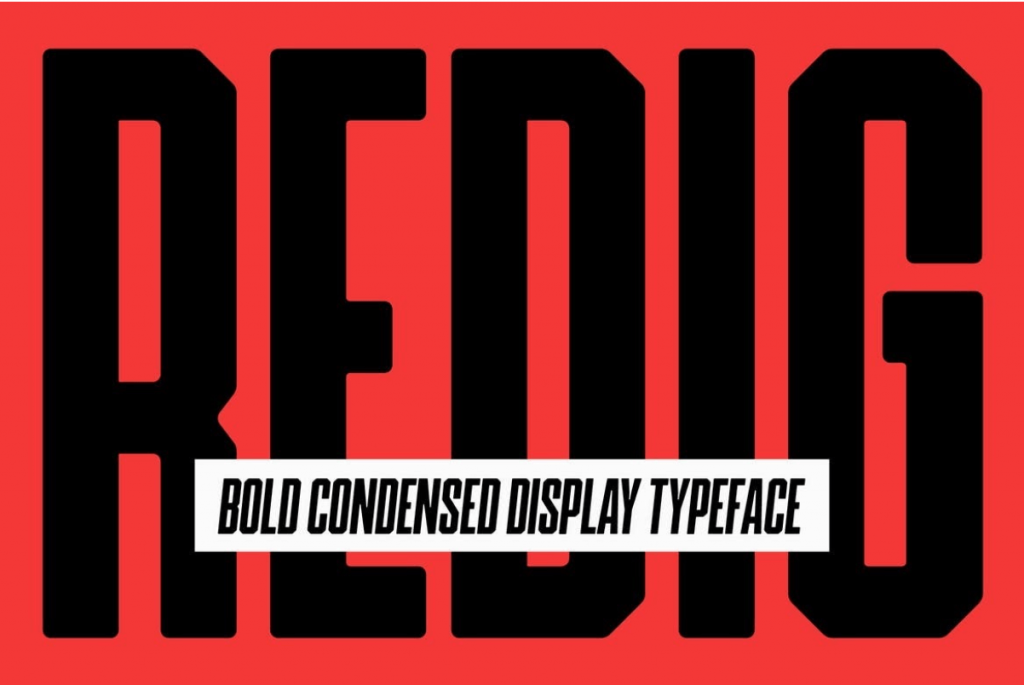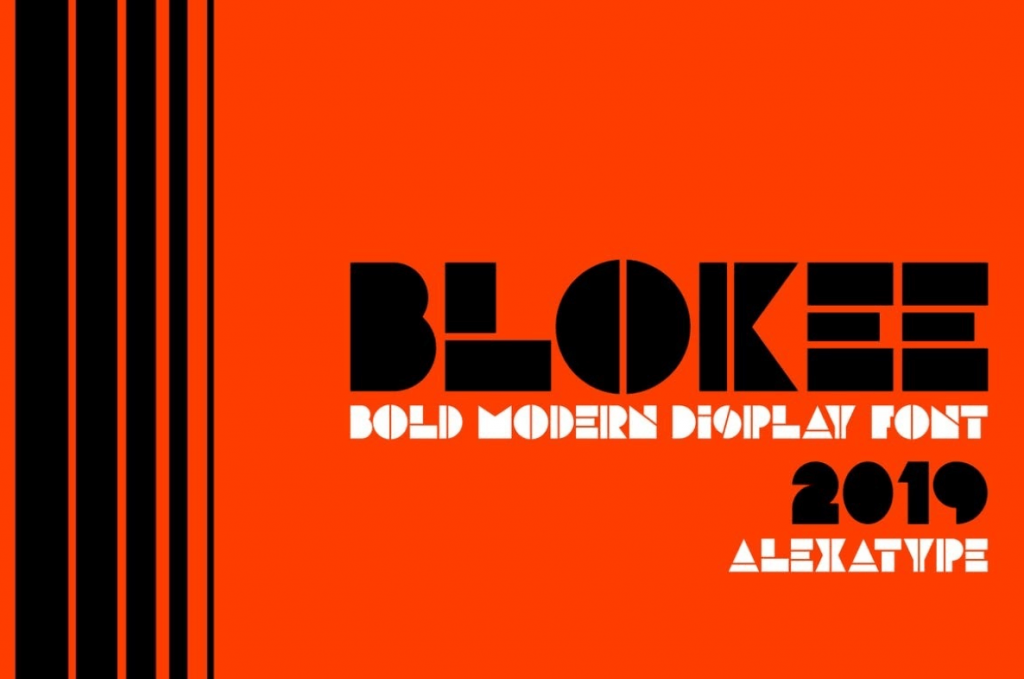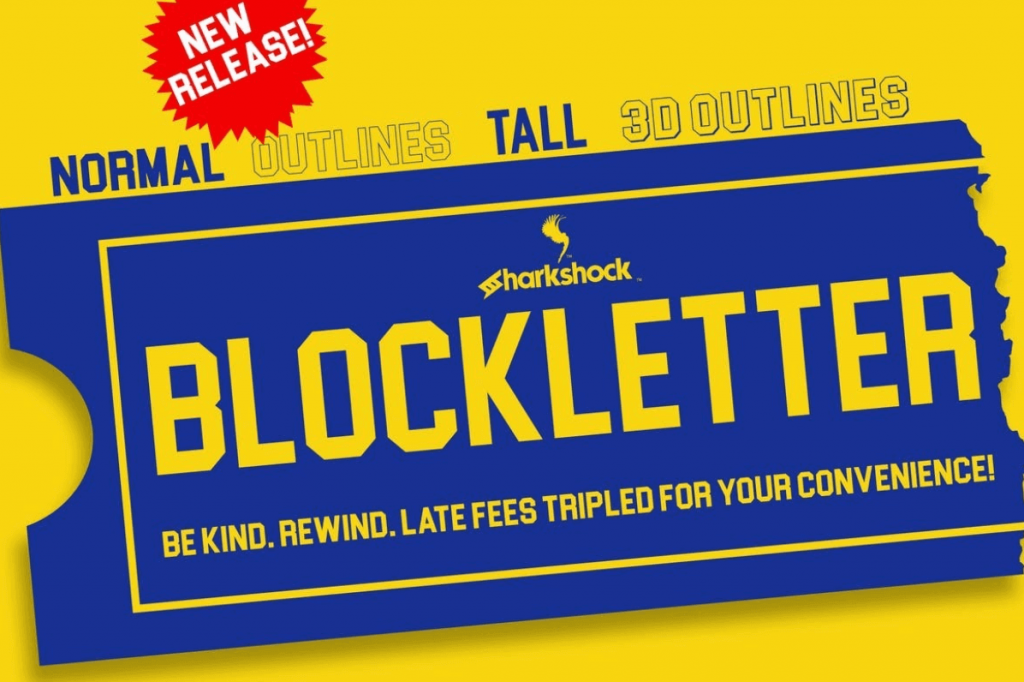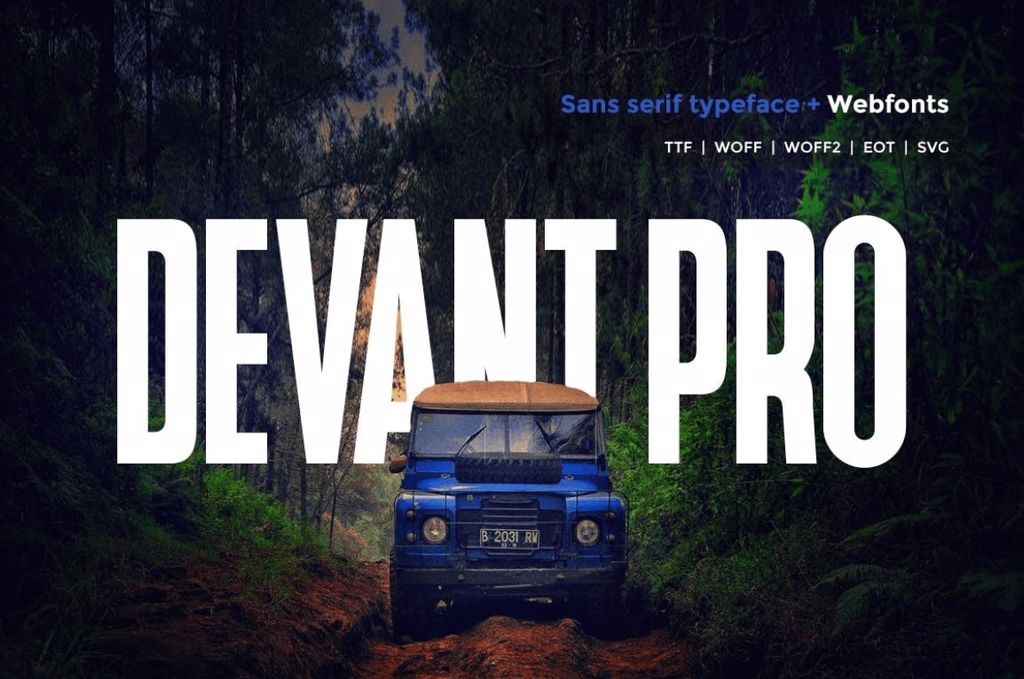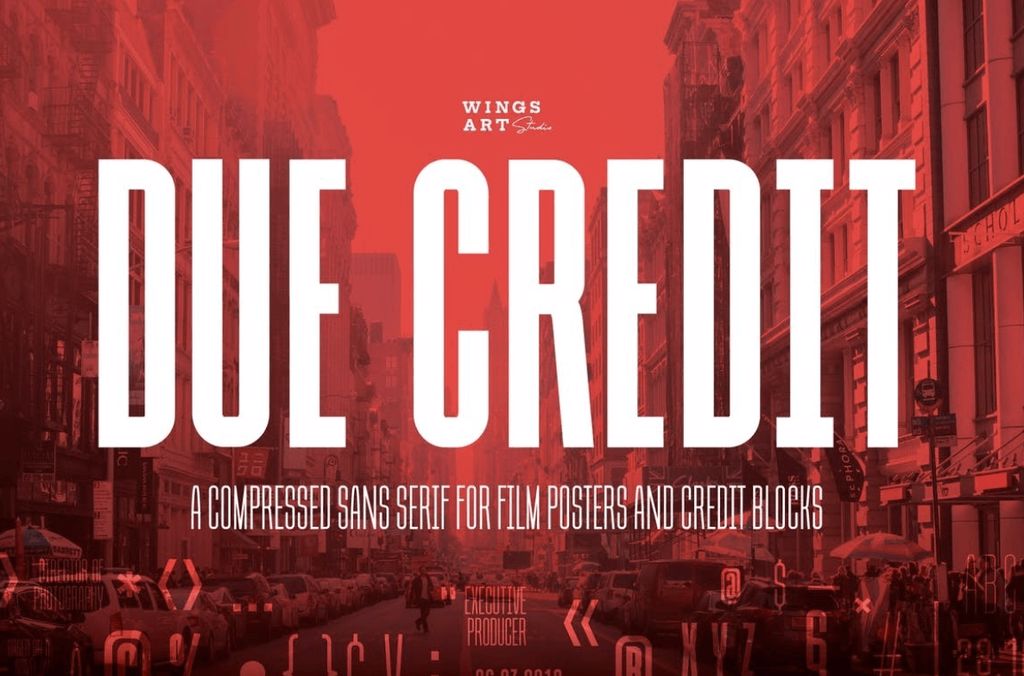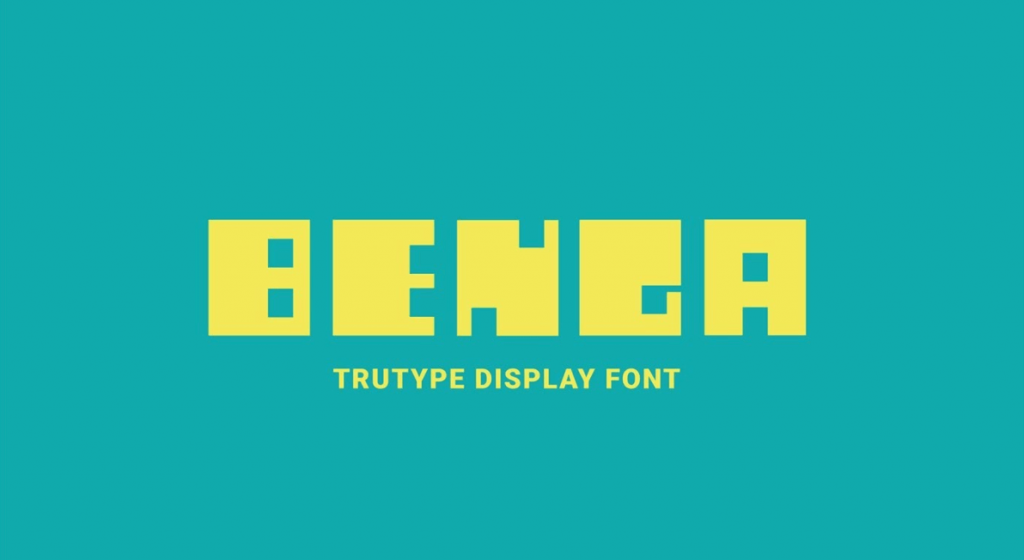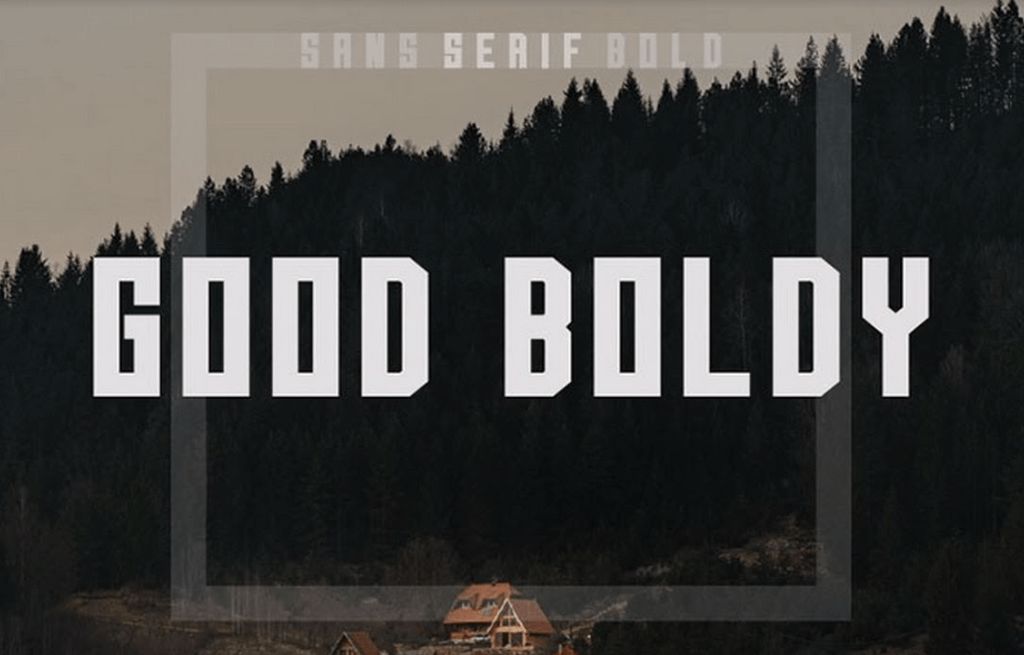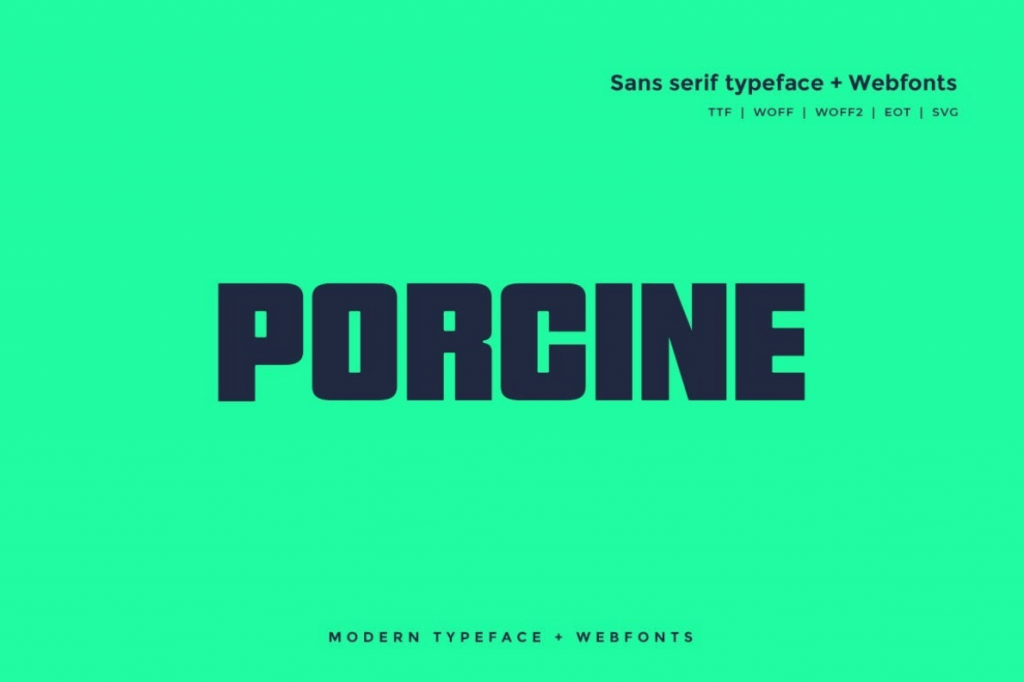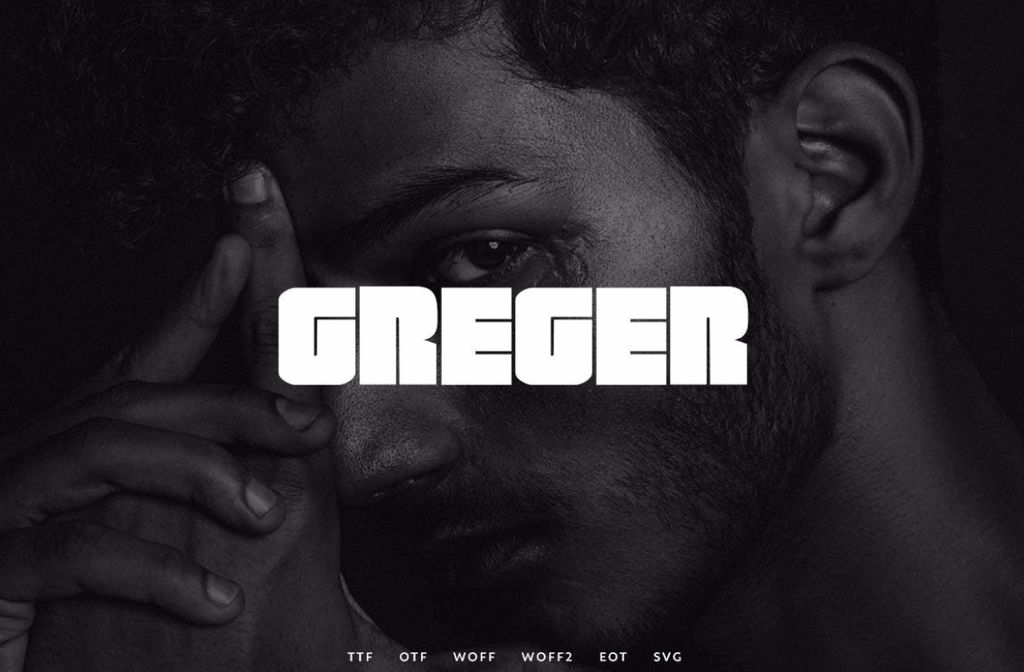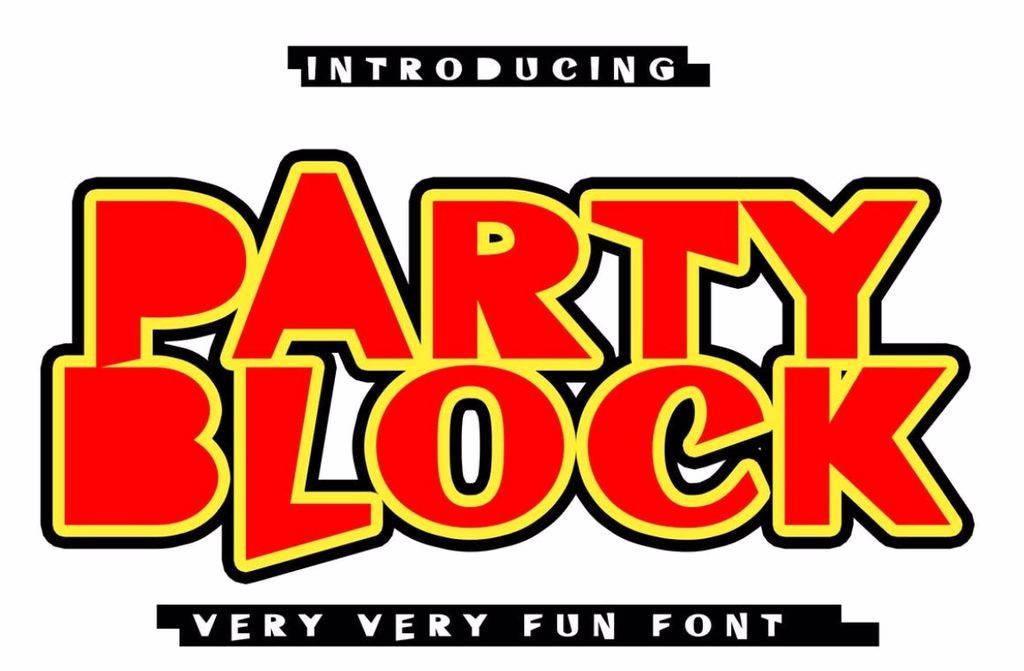
Шрифты с печатными буквами лучше всего подходят для оформления заголовков, так как они хорошо читаются на расстоянии, а также привлекают внимание пользователей.
Такие шрифты в основном используются для дизайна плакатов, флаеров и логотипов. Вопреки всеобщему мнению они могут быть не только квадратной блочной формы, но и любой другой.
В этой статье мы рассмотрим 13 лучших шрифтов с печатными буквами, которые вы можете применять как в классических, так и в современных дизайн-проектах.
Шрифт Redig — это отличный выбор шрифта для создания больших заголовков, особенно для плакатов, журналов и газет. Шрифт состоит из толстых печатных букв со слегка изогнутыми краями. Он выглядит смело и ярко, что поможет привлечь внимание ваших пользователей.
Шрифт Blokee выполнен в геометрическом стиле с ярким дизайном букв. Он идеально сочетается с заголовками на тему технологий и развлечений.
Шрифт Blockletter вдохновлен знаменитым логотипом компании Blockbuster. У него такое же жирное начертание и цвета — синий и желтый. Если вы работаете над постером в ретро-тематике или хотите добавить ностальгическое настроение в ваш дизайн — используйте Blockbuster.
Devant — это современный блочный шрифт с высокими и узкими буквами. Он доступен в нескольких форматах, включая версии OpenType, TrueType и WebFont, что позволяет использовать его для создания заголовков в любом дизайн-проекте. Devant — это отличный шрифт для создания заголовков веб-сайтов, а также плакатов и баннеров.
Due Credit — это шрифт с заглавными буквами, который представлен в двух стилях с разной толщиной шрифта. Он особенно подходит для постеров фильма, а также для блока титров. В качестве бонуса вы можете скачать дополнительный шрифт в дизайне «Horror».
Benga — это бесплатный блочный шрифт с уникальным дизайном букв очень толстого начертания. Его дизайн вдохновлен ретро-видеоиграми, что придает этому шрифту игривый и необычный вид.
Good Boldy — это еще один бесплатный шрифт для печатных букв с лаконичным дизайном. Он будет отлично смотреться как на загруженном фоне, так и в качестве отдельного заголовка. Этот шрифт хорошо подойдет для делового и профессионального дизайн-проекта.
Porcine — это отличный шрифт для создания заголовков для веб-сайтов, флаеров или плакатов. Благодаря засечкам и легкой форме букв, он выглядит очень современно. Этот шрифт доступен в нескольких форматах, включая версии OTF, TTF и Web Font.
Greger — это еще один уникальный блочный шрифт с набором стильных букв. Современный дизайн шрифта поможет выделить заголовки в вашем дизайн-проекте. Этот шрифт отлично подойдет как для логотипов, так и для баннеров и плакатов.
Party Block — это необычный шрифт с жирным блочным дизайном букв. Он идеально впишется в креативный дизайн флаеров и плакатов для вечеринок. Он также подойдет для различных печатных дизайнов, таких как поздравительные открытки и сувенирная продукция.
Шрифт Deep Block поможет сделать дизайн вашего проекта особенным. В его наборе печатные буквы с необычным дизайном и жирным начертанием. Deep Block — это отличный шрифт для создания музыкального плаката или обложки компакт-диска.
School Mania — это блочный шрифт с трехмерным буквенным дизайном. Буквы нарисованы от руки, поэтому лучше всего использовать School Mania в дизайн-проектах, которые связаны с детьми и школой. Шрифт состоит из заглавных, прописных и строчных букв.
Freebies — это бесплатный блочный шрифт с уникальным футуристическим дизайном. Он идет вместе с набором креативных букв, которые представлены в виде различных геометрических форм. Шрифт можно использовать как в личных, так и в коммерческих проектах.